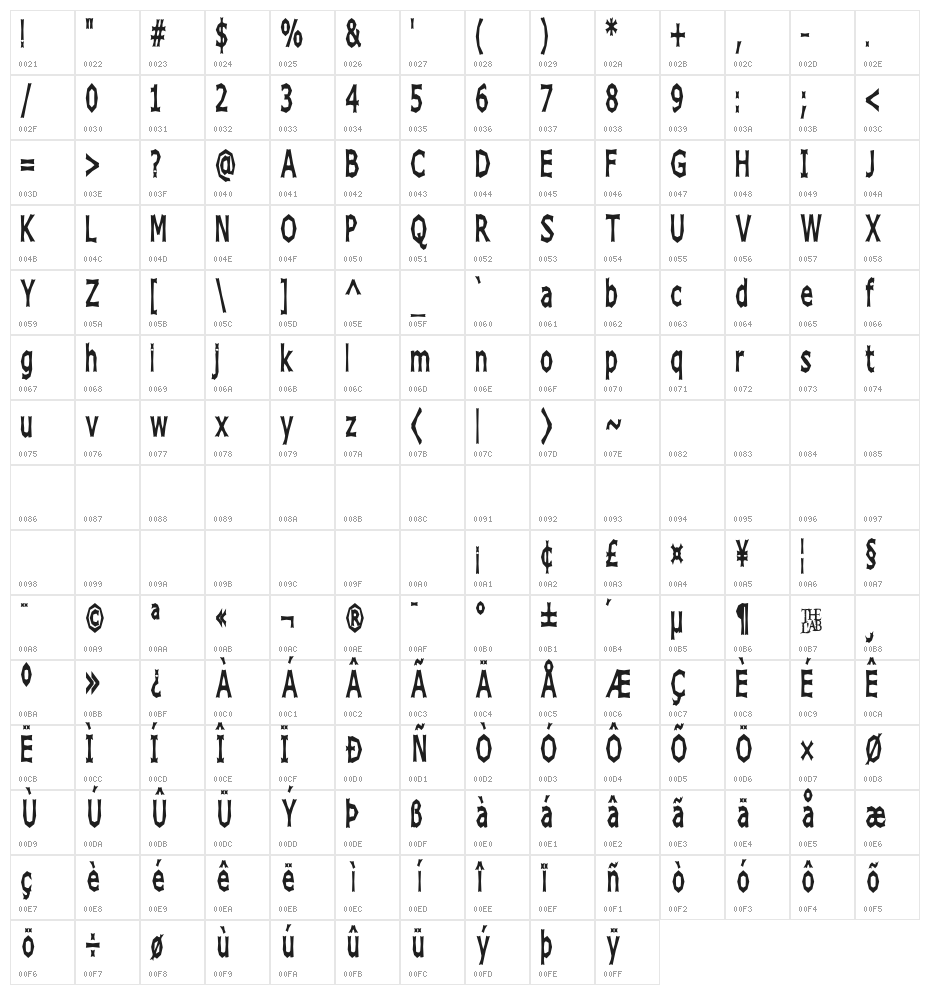
Chizz High Font
| Gesamtstil | Modern, Decorative |
| Vorgeschlagene Projekte | Perfect for posters, album covers, branding, and any project needing a bold, edgy look. |